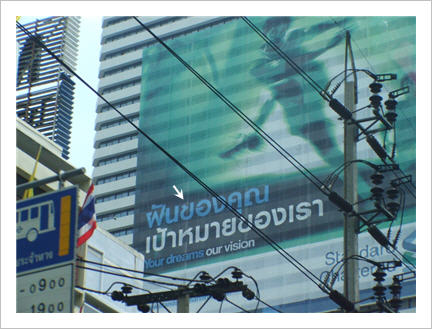
ฟอนต์ไม่เหมาะ
อยู่ดีๆ ก็นึกได้ว่านี่เว็บฟ๐นต์  :31:
เคยโชว์ฟอนต์เจ๋ง ฟอนต์ประทับใจ ฟอนต์ที่น่าจะเอามาทำฟอนต์กันไปแล้ว
ไหงไม่โชว์ตัวอย่างการนำตัวอักษรไปใช้แบบไม่ค่อยเหมาะบ้างล่ะครับ
คิดเสียว่าเอาไว้แบ่งปันความรู้กัน เพื่อขัดเกลาต่อมไทพ็อกกระฝิกันหน่อย
ตัวอย่าง
บิลบอร์ดขนาดใหญ่นี่ตั้งอยู่ริมถนนพระรามสี่
ขับมาจากทางด่วนเลี้ยวขวาแยกคลองเตย หันไปทางสวนลุมก็เจออยู่ด้านซ้าย
รู้สึกว่า ข ไข่มันแปลกๆ เหมือน ย ยักษ์มากเลย
เหมือนเขาเอากิติธาดามาใช้ไม่เหมาะกับป้ายใหญ่ๆ ยังงี้ยังไงไม่รู้ครับ
คงเป็นเพราะมุมที่เราดูป้ายครับ  :42:
ไอ้พวกป้ายโฆษณาขนาดใหญ่ๆ น่าจะใช้ฟอนต์ที่อ่านง่ายๆ เพราะคนขับรถผ่านแว๊บๆ จะได้อ่าน และเข้าใจง่ายๆ ไม่ต้องตีความหมายอีก
อ๋อ ผมมองตั้งกะข้ามแยกจนรถขับผ่านไปถึงตรงนั้นเลยครับ (พอดีน้องแฟนขับ)
กว่าจะควักกล้องออกมา ประกอบเลนส์ แล้วก็เปิดกล้อง รอเครื่องบูต ยันถ่ายเสร็จ นานใช่ย่อย
ซึ่งการนี้แสดงให้เห็นว่ามุมมองของผมที่น่าจะเป็นลูกค้า กลุ่มเป้าหมายของป้ายนี้เห็นปั๊บอ่านไม่ออกเลยในทันที
ยังงั้นก็สอบตกแล้วใช่มะ
สีที่ใช้ด้วยครับ  ผมอ่านแถวล่างไม่ออก  ไอ้ที่สีฟ้าๆหนะ
มีอันนี้แทรกพอขำขำ เพราะเป็นดีไซน์ของเขา
พอดีป้ายมันอยู่ตรงห้องน้ำติดกับบ้านผีสิงของดรีมเวิลด์น่ะครับ
เห็นแล้วกล้าขี้กันไหม  :42:
:30: ประมาณว่า  :24: ไป มองซ้ายมองขวาไป คงทำเพราะคิดว่ามันจะเข้าบรรยากาศบ้านผีสิง
อ๋อ เข้าใจแล้วครับว่าลุงอ๋าห์อาจจะเข้าใจจุดประสงค์ผิด
ในที่นี้ผมจั่วหัวไว้ว่า "การเอาตัวอักษรไปใช้แบบผิดๆ"
(ทีแรกว่าจะขีดเส้นใต้คำนี้ไว้แล้วแต่ลืมได้ไงไม่รู้)
ยังงี้เคลียร์ไหมครับ ถ้าไม่ จะได้พิมพ์ยาวๆ
ผู้ออกแบบ,เจ้าของงาน หรือคนที่มีส่วนได้ผลประโยชน์ เข้ามาเห็น
กลัวว่ามันจะไม่ดี
อ้างคำพูดจาก: ภูกระดึง เมื่อ 22 มิ.ย. 2006, 11:52 น.
เข้าใจจุดประสงค์แอน
พี่แค่ถามๆดูน่ะ
และเห็นว่าไม่เหมาะที่จะเปิดให้วิจารณ์กันในที่สาธารณะอย่างนี้
เว็บฟ๐นต์ก็ออกจะดัง มีคนอ่านเยอะแยะ
ผู้ออกแบบ,เจ้าของงาน หรือคนที่มีส่วนได้ผลประโยชน์ เข้ามาเห็น
กลัวว่ามันจะไม่ดี
ป่านนี้คนทำป้ายนั้นคงเห็นแล้วแหละ  :43:
รับไว้พิจารณาครับ
คนอื่นว่าไงเอ่ย
เอาไงดี ผมมองในแง่ของกรณีศึกษาที่เกิดประโยชน์ต่อผู้คนรุ่นหลังที่จะนำไปใช้น่ะครับ
เหมือนกับสร้างหนังมาเรื่องนึง (สายนิเทศเหมือนกัน) ก็ต้องมีการยอมรับคำวิจารณ์ได้
สร้างงานโฆษณามาเรื่องนึง ก็ต้องยอมรับคำวิจารณ์ได้
ถ่ายภาพมาภาพนึง ก็ต้องยอมรับคำวิจารณ์ได้
รังสรรค์งานศิลปะขึ้นมาชิ้นนึง ก็ต้องยอมรับคำวิจารณ์ได้
ดังนั้นในที่นี้-วงการออกแบบเพื่อการสื่อสาร-ถ้าสมมติมีใครไปเห็นงานที่ทำออกมาแล้วสะดุดใจ (โดยเฉพาะในทางการศึกษา)
ก็ควรมีสิทธิ์ที่จะแสดงความเห็นในเชิงวิจารณ์ได้
แต่ในกรณีของเลือดสถาปนิกอันนี้ผมก็เข้าใจครับพี่ว่าวงการนี้คนน้อย
และจำเป็นอย่างยิ่งที่จะต้องมีกฏที่เอาไว้ให้อยู่ร่วมกันอุ่นๆ นานๆ เลยต้องมีการร่างกติกาที่พี่ว่าเอาไว้
ถูกผิดประการใด กรุณาชี้แนะด่วนใน 5 นาทีครับ
อ๊ะ ลืมไป ต้องเรียกว่าลุง
ถึงถามไงว่า มีกฎหรือข้อบังคับหรือถือว่าผิดมารยาทหรือเปล่า
เรื่องการวิจารณ์งานของวิชาชีพออกแบบกราฟิคดีไซน์
ถ้าไม่มีก็ไม่เป็นไรมั้ง